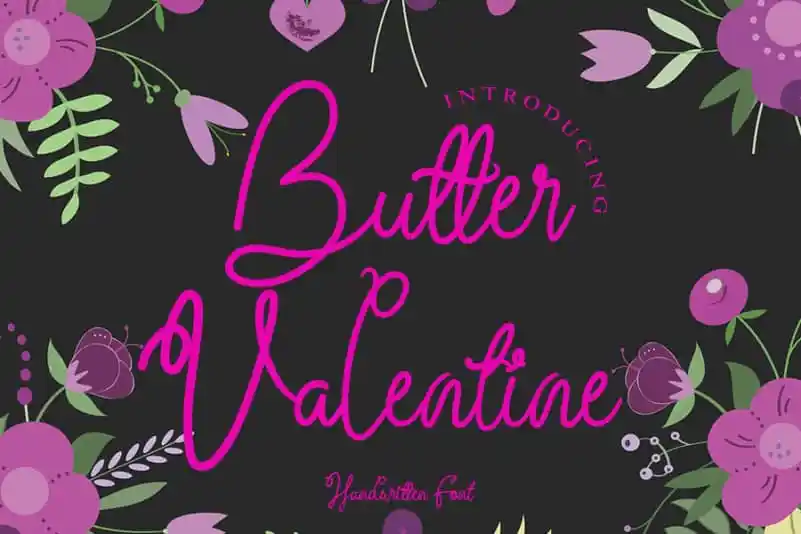
Butter Valentine Handwritten Font – Download Grátis
A Butter Valentine Handwritten Font é uma elegante escolha para aqueles que buscam um toque romântico e leve em seus designs. Ela cria um ambiente envolvente, especialmente atraente para uso em cartões de casamento, cartinhas de agradecimento, citações e cartões de boas-vindas. Sua graça natural se destaca em logo e cards de negócios ou em qualquer outro projeto que esteja em busca de um toque personalizado. O design da fonte não apenas enriquece seu design final, mas também adiciona uma sensação única de sofisticação e delicadeza ao mesmo tempo. Com sua versatilidade para diferentes tamanhos e formatos, a Butter Valentine Handwritten Font pode transformar qualquer projeto em um trabalho de arte cuidadosamente elaborado.